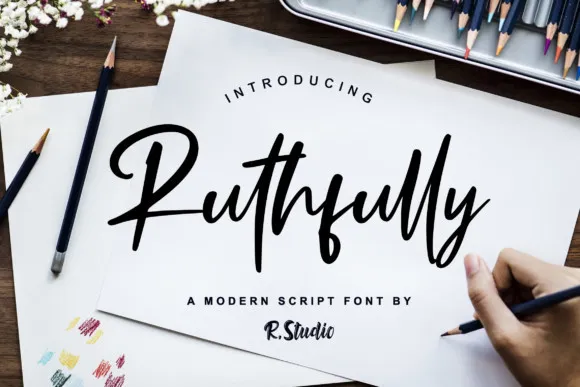
Ruthfully Handwritten Font – Download Grátis
Esta é uma fonte de escrita cursiva que serve como um autêntico selo pessoal com um toque contemporâneo e contemporâneo. É perfeita para projetos variados, desde as mensagens, logotipos, cabeçalhos de blog, posters até camisetas, roupas de praia, cartões de convite e materiais de papelaria. Ruthfully Font transmite elegância através da simplicidade moderna e garante um charme único para seus projetos. Seja para uma publicação em seu site ou uma criação gráfica em casa, Ruthfully é a fonte perfeita que lhe permitirá expressar sua personalidade de maneira única. Não hesite em explorá-la nas muitas possibilidades de uso desta beauté escrita por mãos humanas.